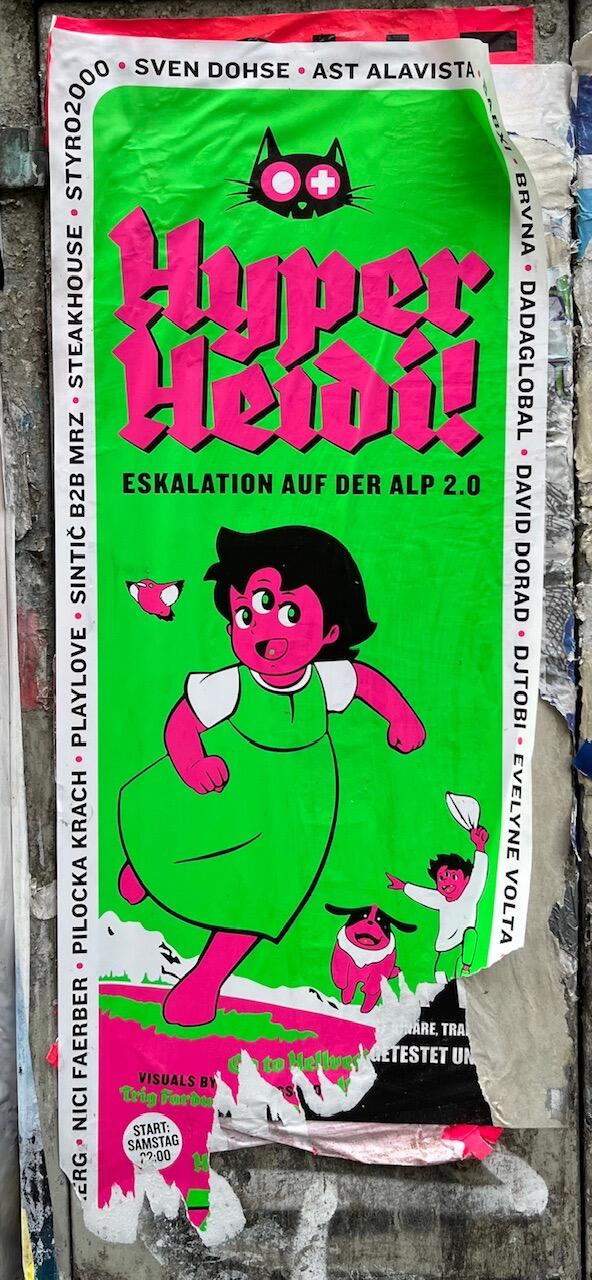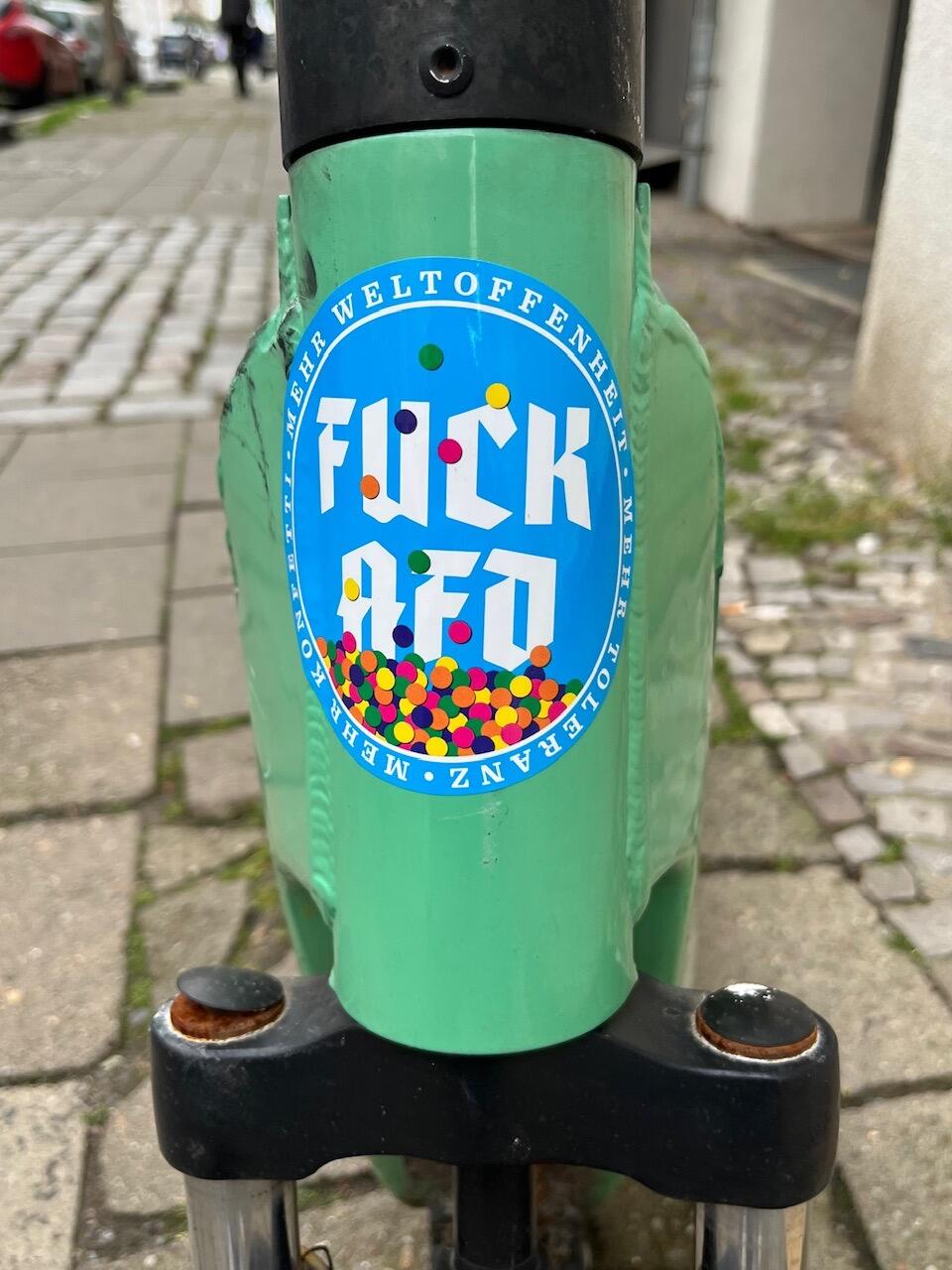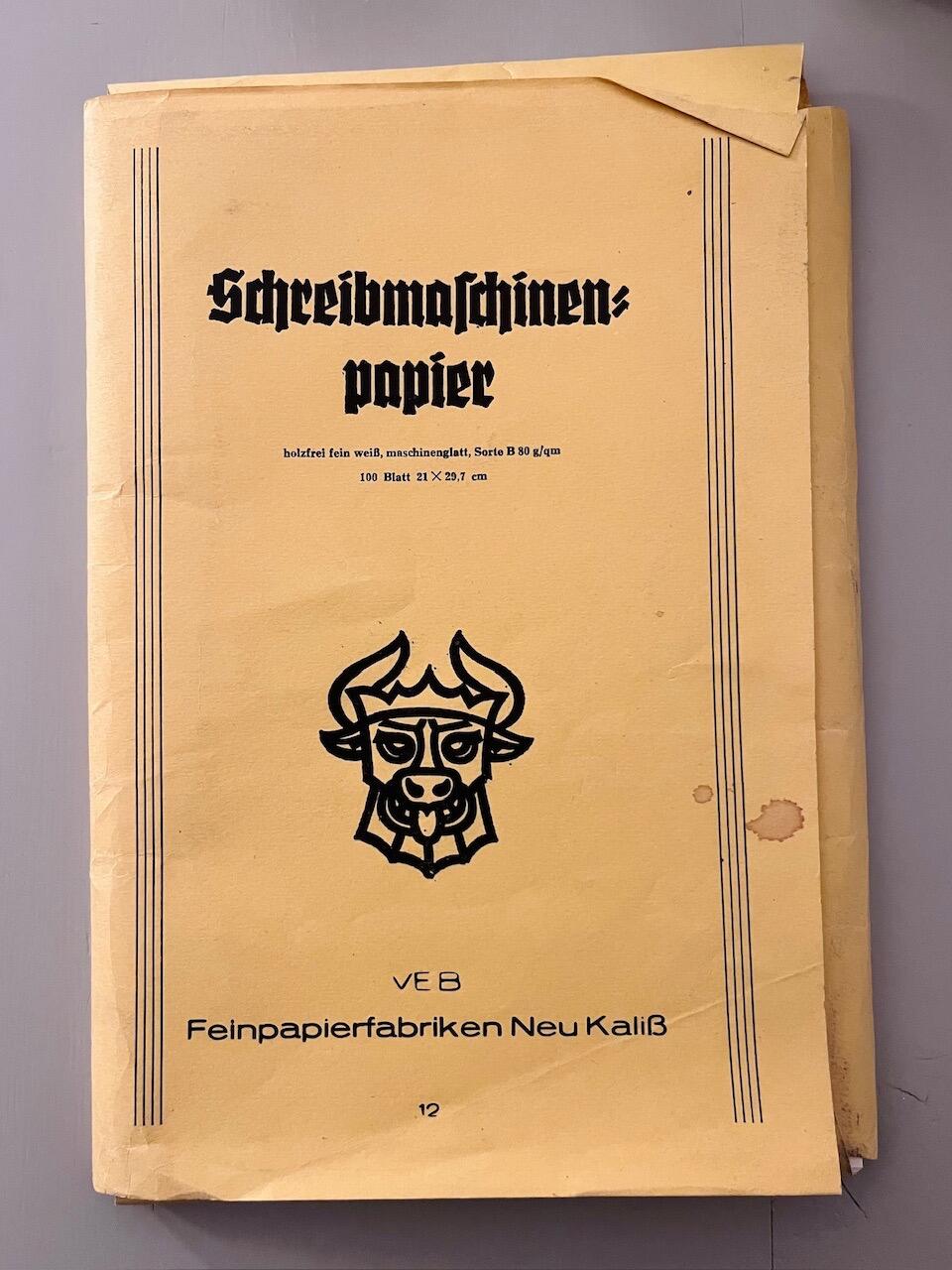
Schaftstiefelgrotesk?
Hier mal ein Heftchen bei dem eine »moderne« Fraktur passte und eingesetzt wurde. Zur besseren Ansicht herunterladen und als Doppelseiten betrachten ...
Ein ehemaliger Professor (und jetzt treuer Kunde von mir) verwendet einfach für alles (außer Umschrift und Arabisch) solche Schriften, auch in Mails;
In der 10. Klasse entdeckte ich Kurrentschrift. Ich lernte eifrig, und war entzückt, daß die winkelige Schreibweise meiner Sauklaue sehr zuträglich war. Plötzlich konnte ich schön und regelmäßig schreiben. So entstanden bald alle meine Notizen "auf Deutsch". Leider kam das zu einem schnellen Ende, denn niemand wollte mir mit meinen Hausaufgaben helfen, weil sie angeblich meine Schrift nicht lesen konnten. So ging es wieder zurück zur Lateinschrift. Einzig das "d" hat überlebt. Obwohl, "überlebt" ist relativ, denn ich kann mich nicht erinnern, wann ich das letzte mal etwas mit der Hand geschrieben habe.
Hehe, danke für den kleinen Einblick in Deine Schreibvergangenheit. :-D Ich schreibe seit ein paar Jahren alle meine privaten Notizen in Kurrent. Das hatte ich mir mal eher aus Langeweile draufgeschafft und dann gemerkt, wie praktisch es ist, wenn man bei längeren Zugfahrten (ich musste eine Zeitlang öfter von Berlin nach Halle, Göttingen und Osnabrück) ganz ungeniert schreiben kann, weil der neugierige Nebenmann es mit ziemlicher Sicherheit nicht wird entschlüsseln können. Und ja, beim Durchblättern sehen meine Notizbücher mit Kurrent sehr viel hübscher aus als mit meiner sonst verwendeten "normalen" Handschrift.
Da sieht man mal, was passieren kann, wenn man auf der Alp zu viel Milch von gentechnisch optimierten Kühen trinkt. Hund und Vogel sind schlauer ...